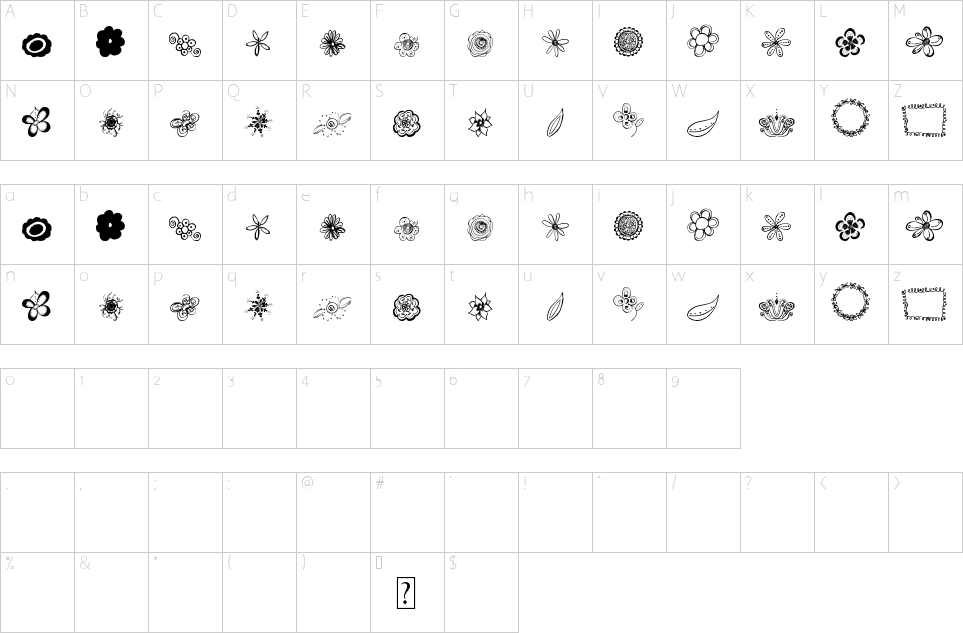
Descubra a elegância do MTF Flower Foodles Font, uma fonte gráfica minimalista e sofisticada disponível gratuitamente para download. Desenhada por Miss Tiina Fonts, esta font é uma delícia para designers e artistas digitais que buscam uma mistura suave entre natureza e arte. Ela combina elementos florais e leves formas geométricas para criar um resultado arrojado, que vai desde rótulos de produtos até designs de websites. Com seu design cuidadosamente elaborado, é perfeito para dar um toque especial a sua próxima criação. Descubra por si mesmo a paleta de cores e formas únicas desta font e descubra como ela pode enriquecer seu trabalho gráfico.